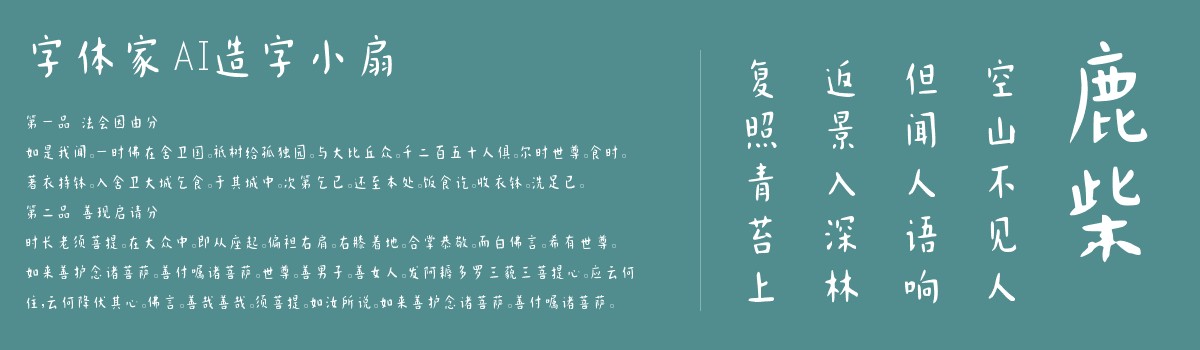
字体家AI造字小扇
字体家AI造字小扇是一款由字体家AI神笔造字生成的艺术字体,此字体笔画温润如玉,边缘柔和无锋棱,起笔收笔似羽毛轻拂,过渡自然无滞涩。粗细变化如呼吸般有韵律,不刻意却和谐,竖画挺拔中带微弧,横画舒展似流云。结构疏朗不局促,笔画间似有若无形的牵连,整体沉静又灵动,像手书时笔尖自然流淌的墨迹,温润里藏着书卷气,柔和中透着从容。适合用于一些广告标题、平面文案、海报标题、网页广告用字的编辑。